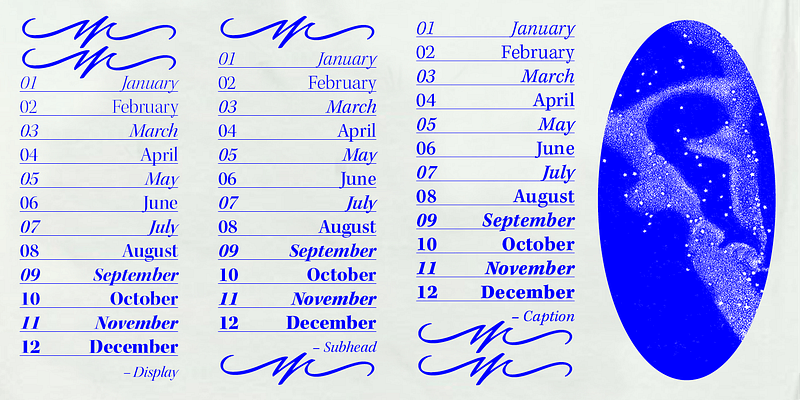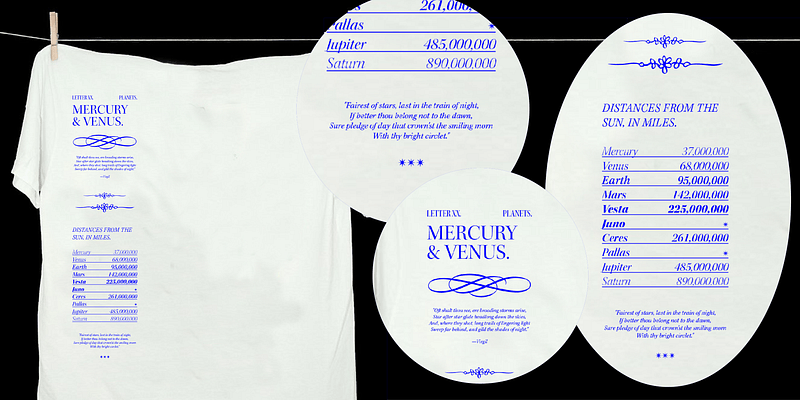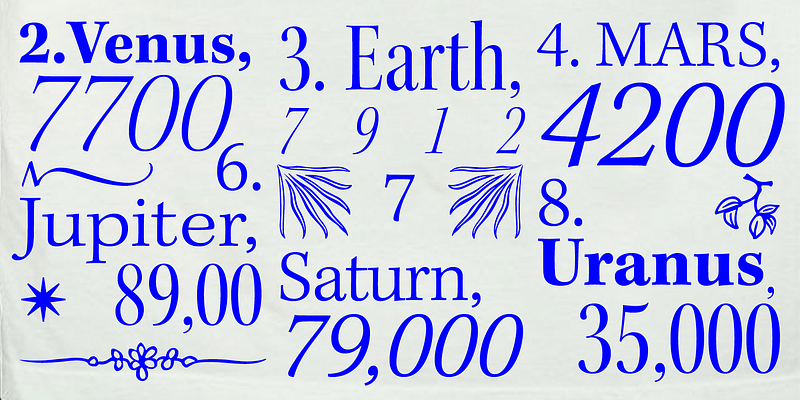
Tirant son nom de l’astronome allemand de la Renaissance, Kepler est une famille de polices contemporaines conçue par le créateur de caractères d’Adobe Robert Slimbach dans la tradition des caractères modernes classiques du XVIIIe siècle. Traditionnellement, les polices modernes sont connues pour leur qualité intellectuelle, mais la police Kepler de Slimbach capture le style moderne d’une manière humaniste. Elle est élégante et raffinée avec une pointe de proportion à l’ancienne et des détails calligraphiques qui lui confèrent chaleur et énergie.